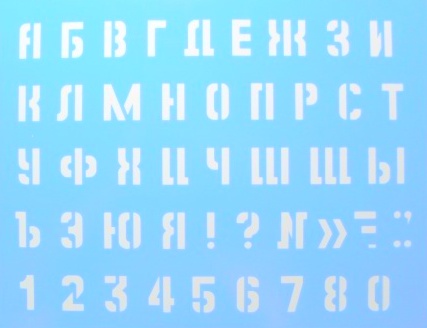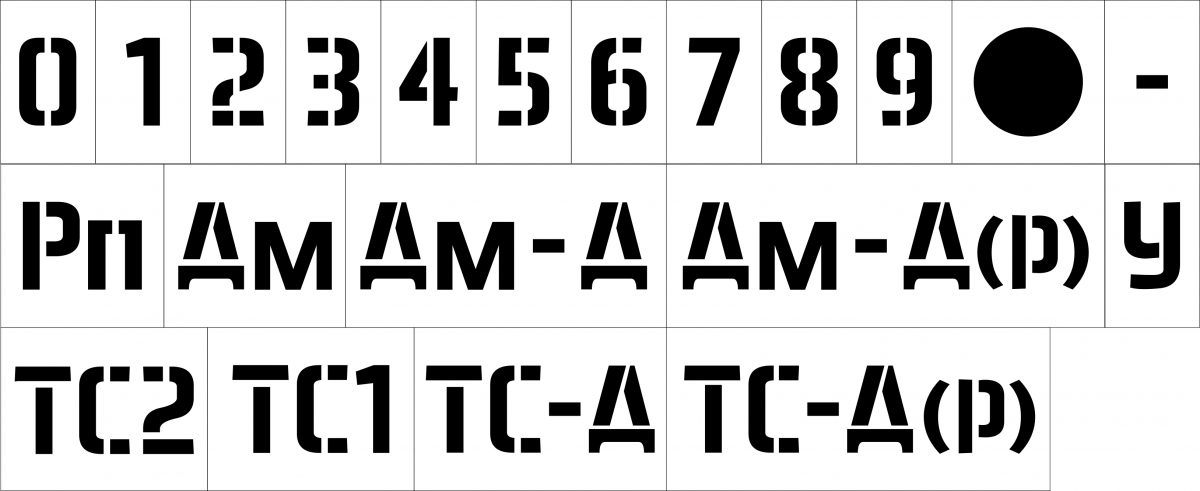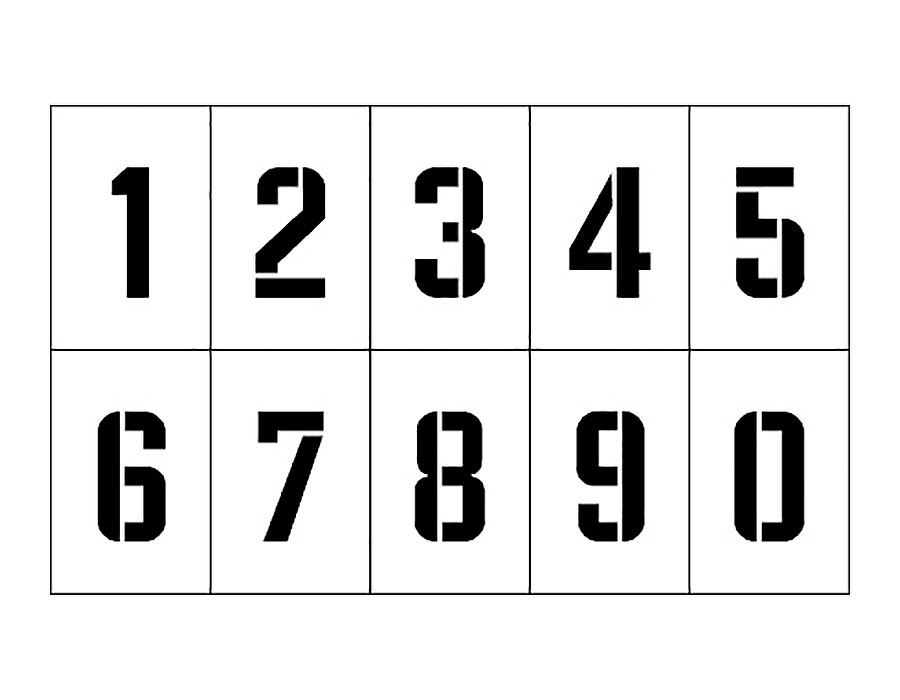
ТРАФАРЕТЫ И ПРИБОРЫ ДЛЯ ВЫПОЛНЕНИЯ НАДПИСЕЙ
При надписывании чертежей применяются трафареты, нормо-
графы и разные механические приборы. Для выполнения тушью букв
и цифр применяют специальные перья: чертежные, воронкообразные,
стеклянные, а также стеклянные трубки и т. д.
Описание чертежных инструментов, перьев и других прис пособ
лений, применяемых при выполнении надписей, а также способов
пользования ими изложено на следующем листе.
Выполнение надписей с помощью трафаретов, нормографоз, ме¬
ханических приборов и прочих приспособлений в некоторой степени
способствует изученчю шрифтов. Применение таких прябороэ вообще
облегчает и ускоряет выполнение надписей.
Однако применение таких приспособлений имеет ряд неудобств
и недостатков.
Главным недостатком является то, что при выполнении надпи¬
сей необходимо иметь в наличии как по размерам шрифтов, так и по
несколько комплектов трафаретов, нормографов и прочих приборов.
Недостатком является еще и то, что этимч приспособлениями можно
в основном пользоваться только при выполнении надписей шрифтами
крупных размеров. В практике же более частое применение имеют
шрифты малых размеров: 5; 3,5 и 2,5.
Кроме того, сама работа трафаретами, нормогра|>ами и прочими
приборами требует приобретения определенных навыков и система¬
тического упражнения.
Изучающим черчение и, в частности, стандартные шрифты зат
руднительно иметь соответствующие наборы нужных приспособлений.
Это могут иметь, и то не всегда, учебные заведения, конструктор¬
ские бюро, проектирующие организации и т. п.
Эти приборы и механические приспособления изготовляются сог¬
борами, если приходится отступать от ширины букв или цифр при
малых размерах места для надписи.
Но основным является то, что шрифт для надписей на черте¬
жах относится к группе рукописных шрифтов, т.
е. при выполнении
надписей буквы и цифры не строятся, а пишутся.
Поэтому изучающие черчение должны обратить
серьезное внимание на приобретение навыков в вы¬
полнении надписей стандартным шрифтом непосред¬
ственно рукой, без использования для этого специ¬
альных сложных приспособлений и приборов. Надо на¬
учиться писать быстро и ясно, но ясность связана с соблюдением
конструкций и размеров букв и цгфр.
Вместе с тем все, что действительно облегчает и механизирует
труд при выполнении надписей, должно применяться.
Надо сочетать умение быстро и четко писать с применением
приспособлений с тем, чтобы максимально ускорять процесс работы.
Некоторые простейшие приспособления дня выполнения надписей
как шаблоны и т. д. можно изготовить самому (см. листы №№ 6 7—71).
Для приобретения навыкоз в хорошем исполнении надписей не¬
обходима систематическая тренировка, при которой следует строго
придерживаться очертаний букв, приведенных в стандарте, сохраняя
пропорции их элементов и последовательность приемов начертания.
Целлулоидные трафареты (порнографы)
Целлулоидные трафареты (нормографы) изготовляются из листо¬
вого целлулоида толщиной 0,8—1,2 мм путем выштамповывання пла¬
стинок в форме прямоугольников с вырезами в виде параллело¬
граммов или с вырезами, соответствующими начертаниям
элементов букв и цифр.
Вырезы в трафаретах выполняются по буквам и цифрам требу¬
емого размера.
Трафареты изготовляются с вырезами для всех размеров согла¬
сно ГОСТ 3454-52. При этом вырезы, соответствующие начертаниям
элементов букв (цифр) для различных алфавитов, выполняются в
отдельности.
В настоящее время выпускаются трафареты, имеющие вырезы,
соответствующие начертаниям элементов букв русского и латинского
алфавитов и арабских цифр.
Трафареты с вырезами в виде параллелограммов можно приме¬
нять для всех алфавитов.
Для того, чтобы во время пользования нормографными перьями
по трафарету тушь не подтекала под ним, к трафаретам приклеи¬
вают с нижней стороны вдоль длинных ребер узкие полосы.
Благодаря
этому, трафарет во время работы по нему не соприкасается своей ра¬
бочей частью (вырезами) с бумагой (калькой) (см. фиг. 1 и 2).
Фиг. 1. Трафарет с вырезами в виде параллелограммов
Если требуется только нанести сетку, т. е. разметить места для
букв с определенными размерами и наклоном в 75° к основанию
строки, пользуются трафаретами с вырезами в виде параллелограммов.
В том месте, где на чертеже надо нанести надпись, предвари¬
тельно проводят каргндашом (Н) тонкие линии. На эти линии нак¬
ладывают соответствующий трафарет (по размеру шрифта) и в про¬
резах трафарета остро очинённым карандашом обводят контуры про¬
резов, т. е. вычерчивают параллелограммы или при определенном на¬
выке по прорезам не метают очертания требуемых букв.